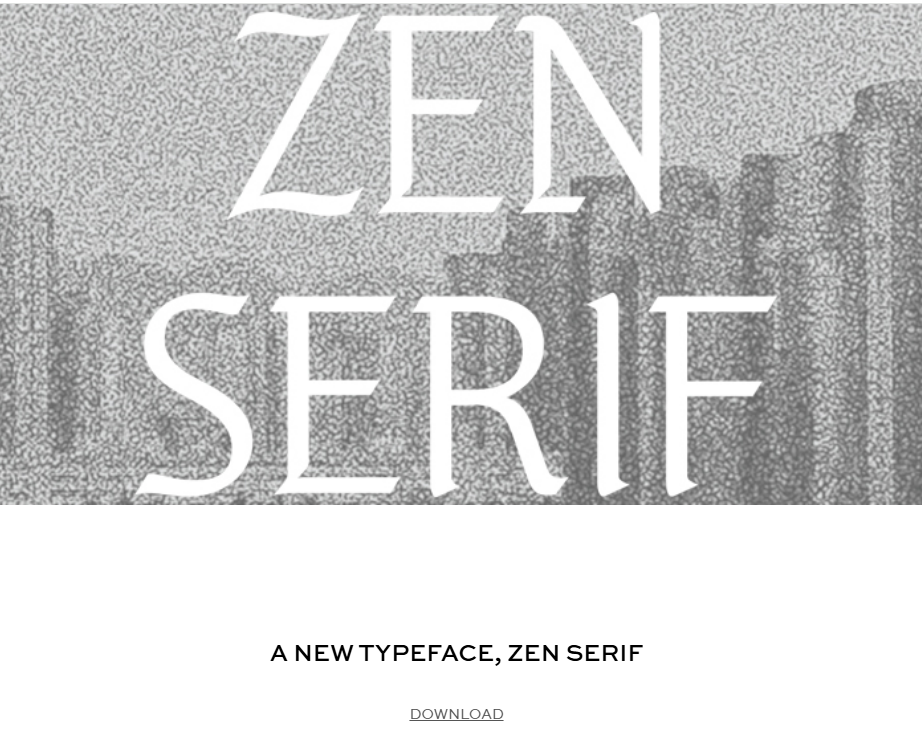
2025년 한글날을 맞이해, 블랙핑크의 제니가 특별한 선물을 팬들과 한글 사용자 모두에게 공개했다. 바로 전통과 현대가 조화를 이루는 독창적인 한글 서체, 'ZEN SERIF(젠 세리프)' 폰트다. 이 폰트는 단순한 연예인 콜라보를 넘어서, 한글의 조형미를 세계적으로 알리는 데 기여하고 있다. 특히 OA엔터테인먼트와 함께한 이번 프로젝트는 디자인뿐 아니라 저작권 측면에서도 자유로운 사용이 가능하다는 점에서 실용성과 가치를 동시에 지닌다. 글을 읽는 독자들은 이 글을 통해 제니의 감성이 담긴 ZEN SERIF 폰트를 안전하게 다운로드하고, 자신의 콘텐츠에 어떻게 활용할 수 있는지에 대해 구체적인 방법까지 확인할 수 있다.
ZEN SERIF(젠 세리프) 폰트란?
ZEN SERIF 폰트는 블랙핑크 제니가 OA엔터테인먼트(ODDATELIER)와 협업하여 제작한 한글 전용 폰트다. 이 서체는 전통적인 세리프 형태의 안정감과 함께 모던한 곡선미를 담아, 누구나 쉽게 문서나 디자인 작업에 활용할 수 있도록 설계되었다.
- 제작 배경: 2025년 한글날을 기념하여, 한글의 조형적 아름다움을 전 세계에 널리 알리고자 제작됨
마무리: ZEN SERIF 폰트를 사용해야 하는 이유
ZEN SERIF는 단순한 글꼴이 아니다. 이 폰트는 한글의 전통적 미학과 K-POP 아티스트의 글로벌 감성을 담아, 디자인과 메시지를 동시에 전할 수 있도록 만들어졌다. 사용자는 이 서체를 통해 블로그, 문서, 프레젠테이션, 포스터, 영상 자막 등에서 차별화된 한글 표현이 가능하다.